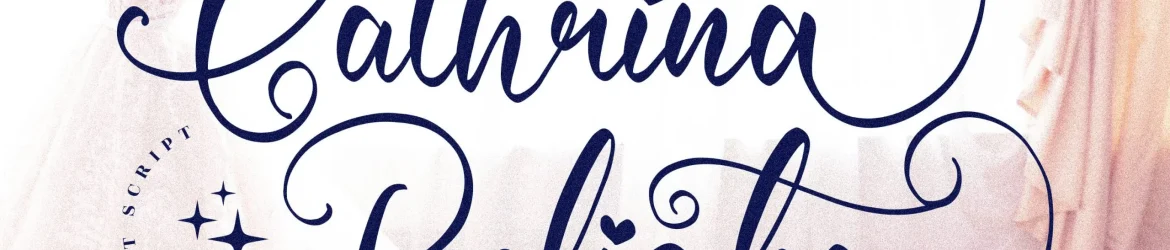
Cathrina Belisha Font – Download Grátis
A fonte Cathrina Belisha é perfeitamente adaptada para projetos que exigem uma escrita romântica e elegante. Seja ela utilizada em logotipos, projetos de marca, designs de móveis de casa, embalagens de produtos, taças, citações, posters, sacolas de shopping, camisetas, capas de livros, cartões de nome, cartões de convidados e cartões de agradecimento, etiquetas, fotografias ou até mesmo marcas especiais. Suave e profunda ao mesmo tempo, Cathrina Belisha é uma escolha perfeita para qualquer projeto que pretenda adicionar um toque delicado à sua criação. Engane-se se pensa que ela apenas serve para projetos de design gráfico; a fonte também se destaca em aplicativos cotidianos como assinaturas de e-mail ou até mesmo cartões de papel, tornando-a uma aliada indispensável na carteira do designer.